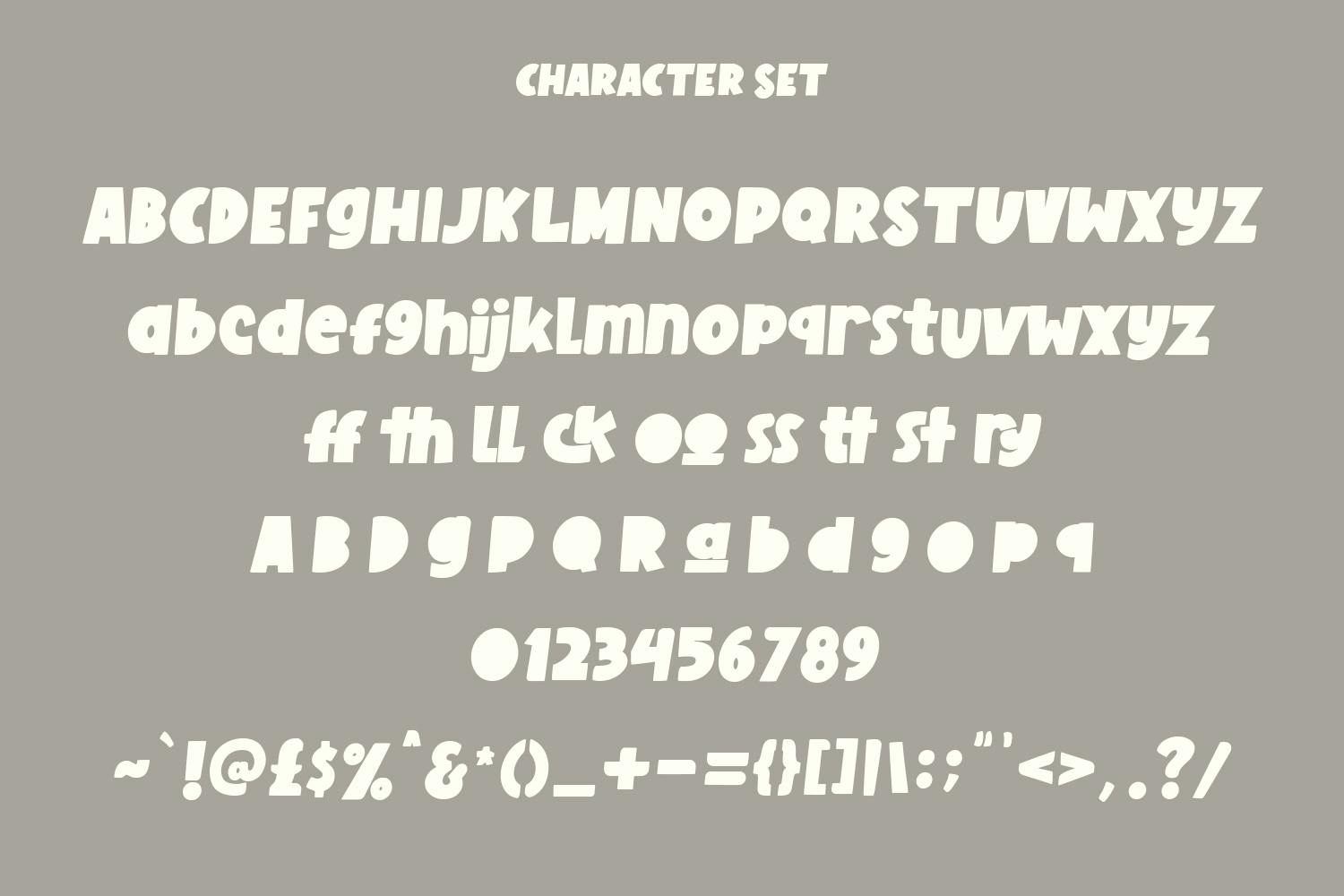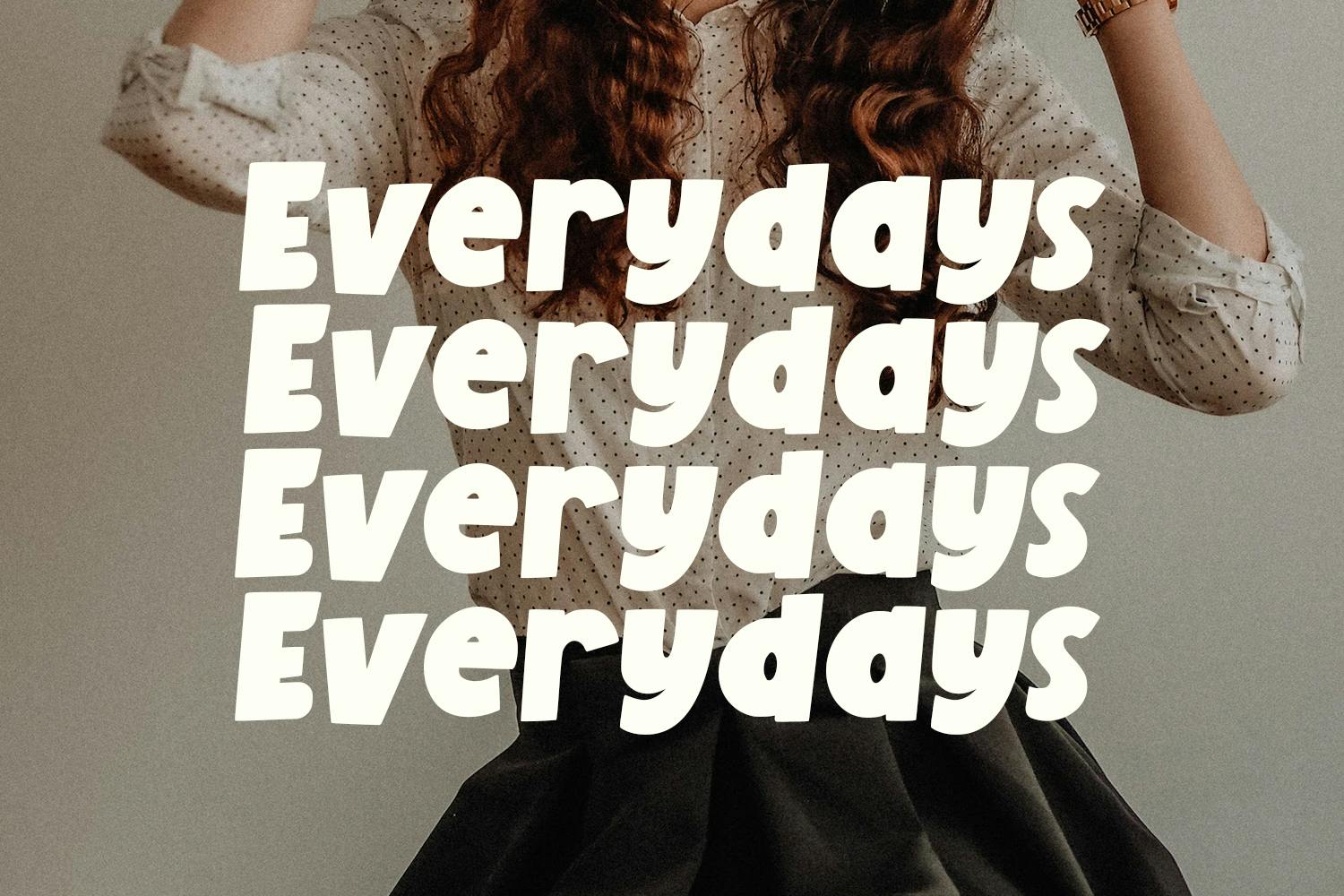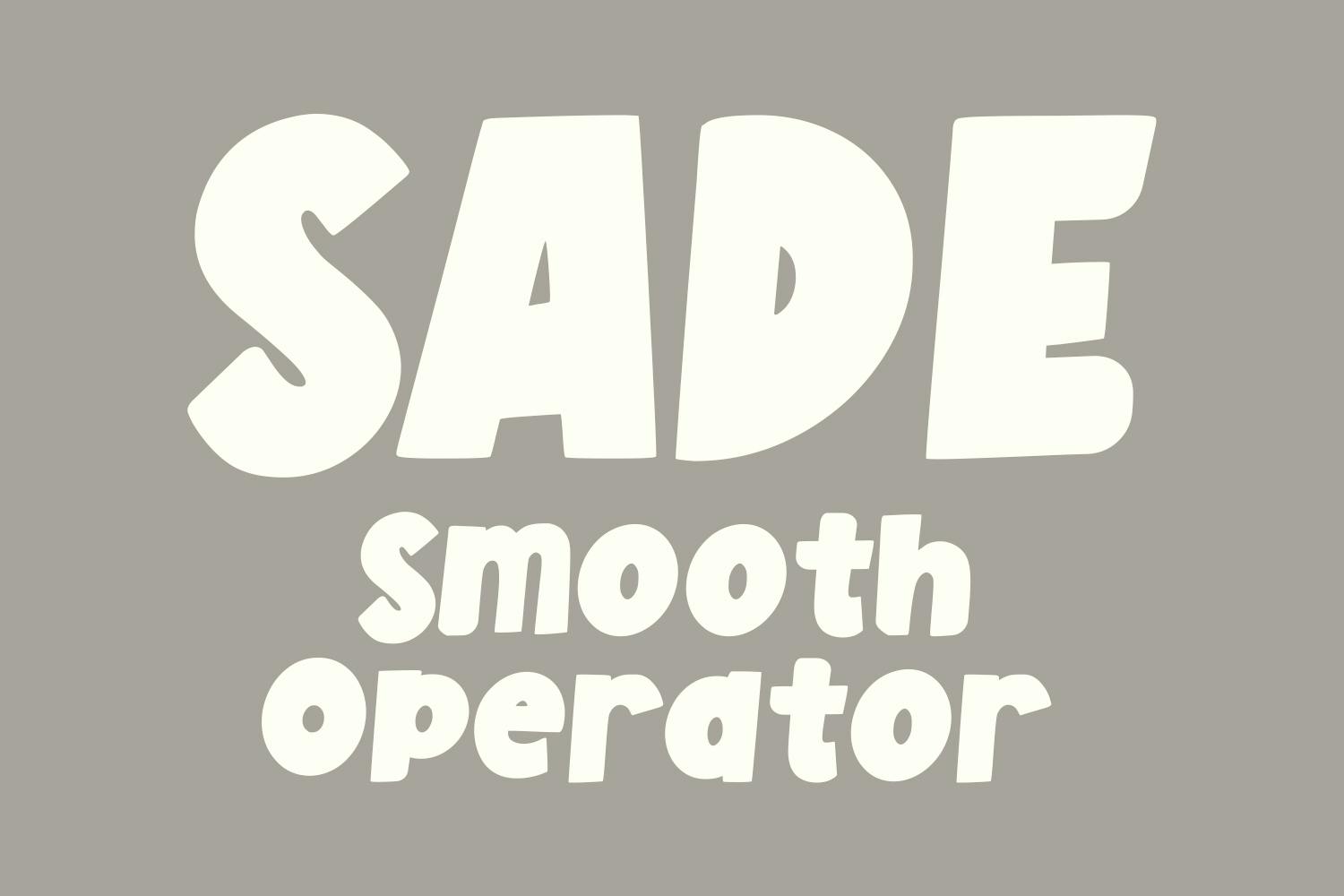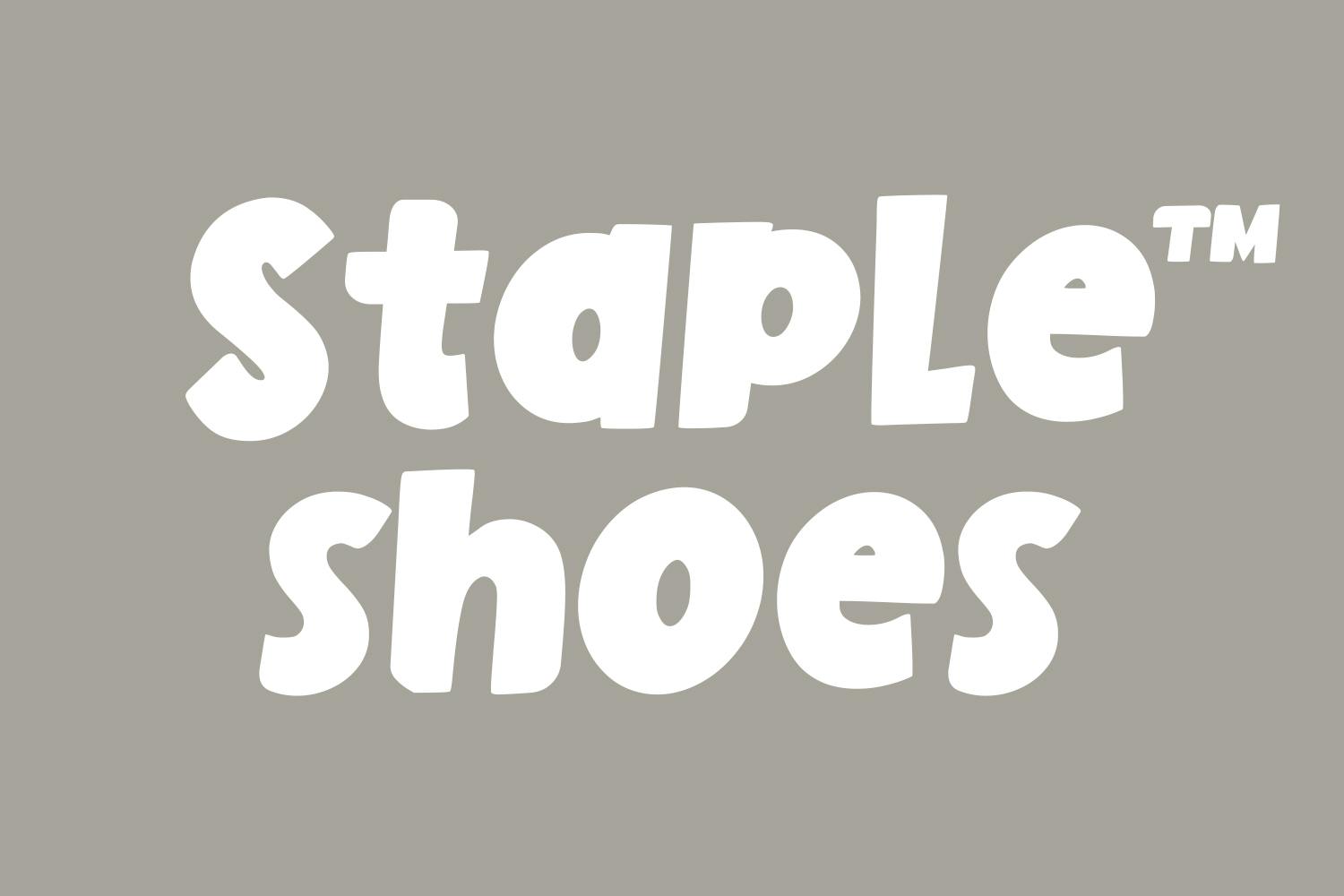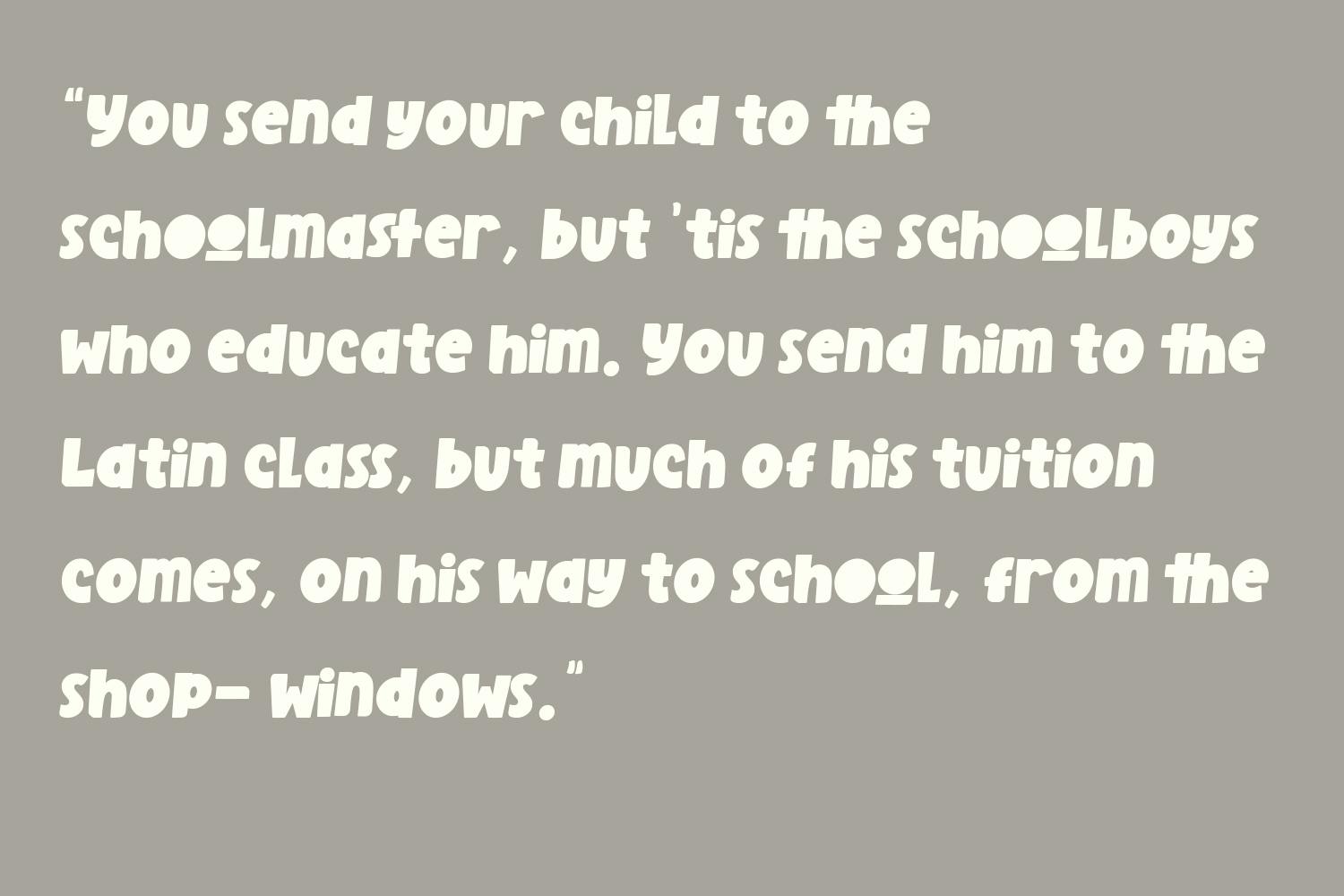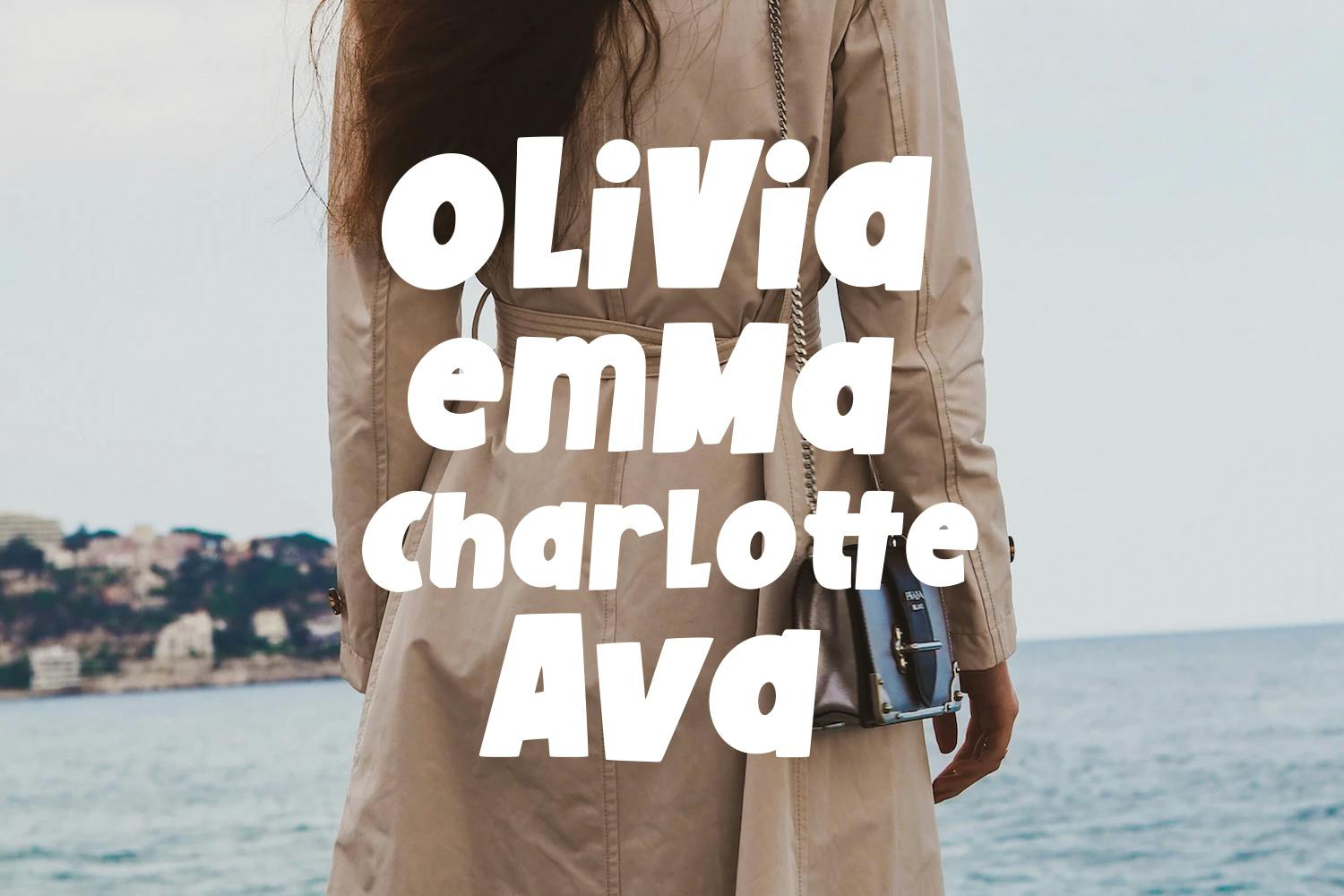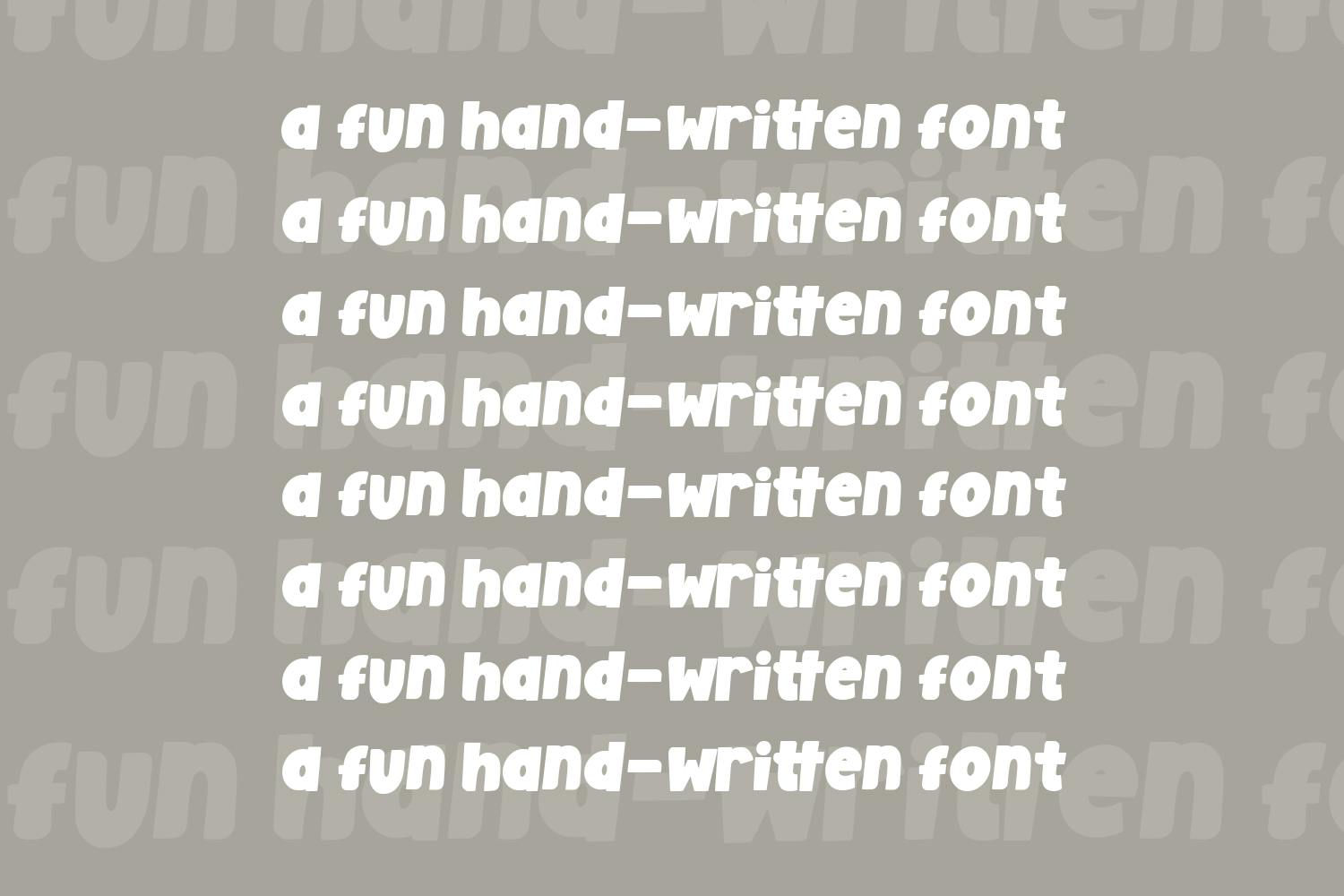
فونت Jeklin یک فونت دستنویس و زیبا با طراحی sans است. این فونت دارای ضخامتهای Bold، شخصیتهای شاداب و ترکیبات و جایگزینهای متنوع است که به شما کمک میکند تا آثار خلاقانهتری تولید کنید. فونت Jeklin از بیش از 100 زبان مختلف پشتیبانی میکند و برای طراحی لوگو، شبکههای اجتماعی، عناوین فیلمها، عناوین کتابها، متنهای کوتاه و حتی متنهای طولانی مناسب است و میتواند به عنوان فونت ثانویه در کنار فونتهای sans یا serif استفاده شود. با فونت Jeklin، آثار خیرهکنندهای خلق کنید.